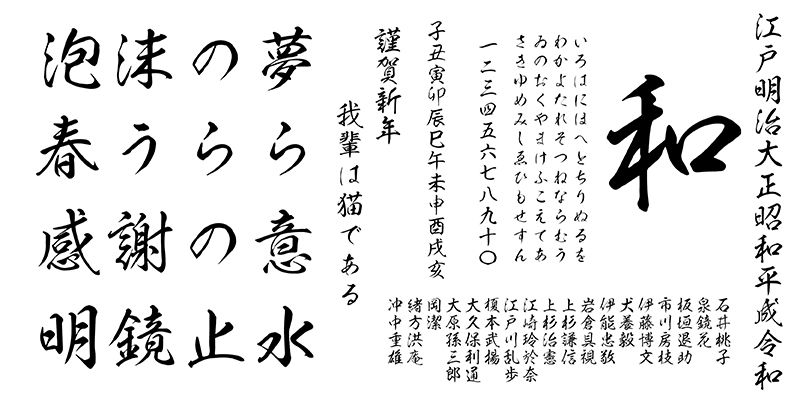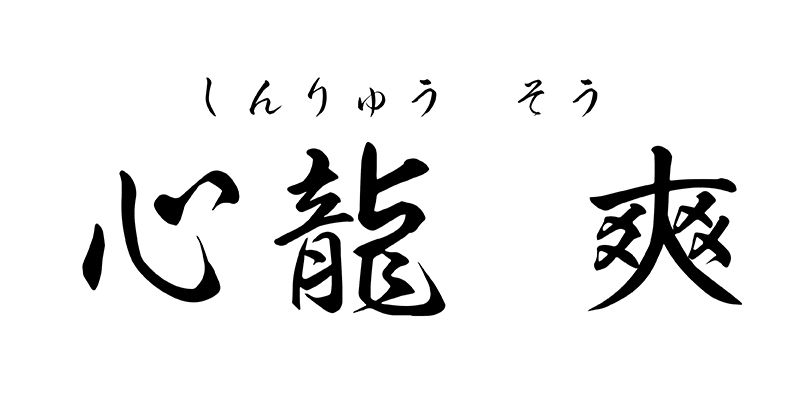
Shinryu — шрифт, имитирующий буквы, написанные кистью, вдохновленный изображением очаровательной девушки-дракона, говорящей с нами. Его тонкие штрихи придают образу мягкости, а тексту — величия.
Kokuryu-sou в Adobe Fonts — это версия Kokuryu с меньшим количеством размытых штрихов, зрительно уменьшающая размер букв. Этот шрифт подходит для вырезания букв, анимации или видеоклипов.
Showashotai
Под брендом Showashotai создаются высококачественные гарнитуры шрифтов, будто написанные кистью. Гарнитуры подходят для различных сфер применения. Форма каждой буквы тщательно разрабатывается опытным мастером каллиграфии.
Изначально, в 1950-х, Kouei Sign Works занималась производством рекламы, позднее, в 2006 г., компания переквалифицировалась и стала специализироваться на разработке гарнитур шрифтов, будто написанных кистью. В 2013 г. компания была официально переименована в Showashotai Co., Ltd. В Showashotai специалисты создают цифровые гарнитуры каллиграфических шрифтов, которые выглядят так реалистично, будто действительно написаны кистью. Компания Showashotai стремится сохранить культуру японской каллиграфии в будущем, выполняя все производственные работы на собственном предприятии.